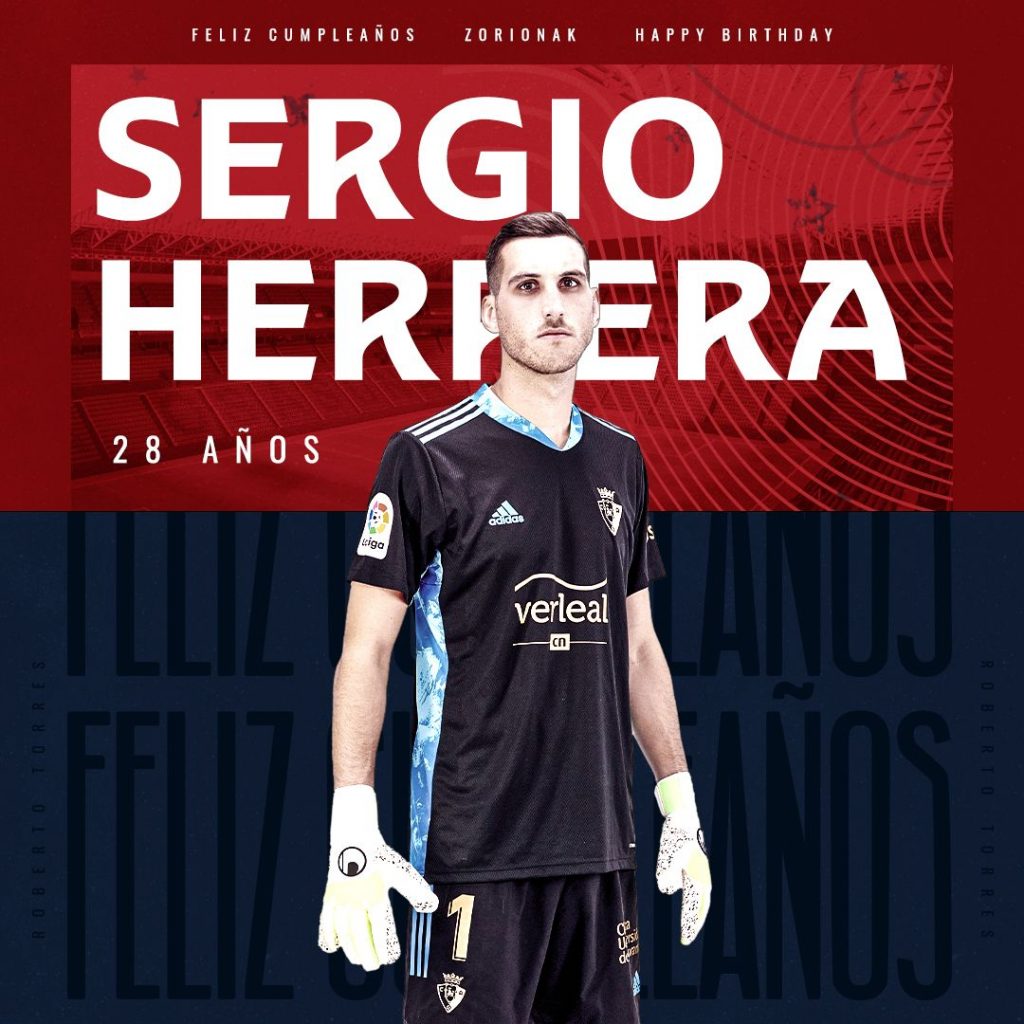
Con motivo del centenario de la entidad, el Club Atlético Osasuna ha estrenado su nueva tipografía realizada por el estudio pamplonés Ashler Design.
Osasuna ha estrenado su nueva tipografía exclusiva (diseño de letras y números) realizada por el estudio pamplonés Ashler Design. Se trata de una tipografía diseñada exclusivamente para el club rojillo y que se ha bautizado como Osasuna Font. El cambio de tipografía no afectará al escudo del club, que seguirá siendo el mismo que hasta el momento.
La nueva tipografía se utilizará a partir de ahora en el logotipo de la entidad, así como en la línea gráfica de la temporada 2021-2022 que también se ha estrenado para redes sociales. Al mismo tiempo, estará presente en diferentes campañas de comunicación que realice el club y tendrá una versión propia para utilizarla en las camisetas oficiales de la próxima temporada cuando la normativa lo permita (amistosos o Copa del Rey, por ejemplo).
Por otro lado, en los partidos de LaLiga no se podrá utilizar. Asimismo, toda la señalética del reformado estadio de El Sadar ya se ha realizado incluyendo las nuevas letras y números diseñados para Osasuna por Ashler Design. «Es la primera vez en su centenaria historia —indican desde el club— que contaremos con una tipografía propia después de haber utilizado en los últimos años diferentes tipos de letras comerciales al alcance de cualquier usuario».
La entidad rojilla pretende actualizar su imagen y hacerlo con coherencia y respeto a sus orígenes, remarcando su identidad propia.
referencias
«Uno de los grandes retos del proyecto —cuenta Octavio Pardo de Ashler— es la falta de referencias históricas claras o literales de las que partir. Osasuna no ha tenido hasta ahora una cultura tipográfica particular y Navarra hasta donde sabemos, tampoco tiene referentes históricos muy claros o conocidos. Ese detalle no es baladí porque Osasuna es más que otra empresa de la zona. Por un lado tiene una ligazón con Pamplona y con Navarra muy profunda; por otro se trata seguramente de uno de los grandes embajadores de Pamplona y Navarra en el mundo sino el que más. Yo siempre cuento la anécdota que cuando viajo por ahí muchas veces cuando me preguntan de donde soy, no conocen Pamplona pero sí conocen Osasuna».
«Por tanto —continua Pardo—, se trataba de afrontar un proyecto de representación identitaria donde había que buscar las referencias en otros medios. El estudio de carteles históricos de los San Fermines y de la feria del toro fue infructuoso, y las conclusiones no fueron tampoco muy claras: estéticamente hablando responden a la tendencia del momento de cuando fueron creados, y en todos estos años de historia no ha habido un elemento formal claro que haya servido de articulador de la línea gráfica. Esto no es en sí mismo un problema sino simplemente constato el hecho. Sí que es cierto que aunque en las primeras propuestas que hice opté por ignorarlos, en la última y definitiva sí que hay algún carácter que se ha inspirado en los carteles, especialmente en los del primer cuarto de siglo».
el euskera
«Otro de los puntos más delicados era el tema del euskera. Como tipógrafo a mí me gusta e interesa mucho la grafía vasca, y creía que esta podía ser una gran oportunidad para implementarla en un proyecto corporativo. También creía que estratégicamente era muy interesante para Osasuna apropiarse de ese espacio gráfico antes que el Athletic de Bilbao, la Real Sociedad o el Alavés —los tres clubes utilizan sans serifs genéricas—. Sin embargo, había varias cosas que no podían obviarse. Por un lado y muy importante, Osasuna no es un equipo vasco, es un equipo navarro».
«Aunque en Navarra el euskera es idioma oficial, no es ni de lejos mayoritario. Al mismo tiempo, Osasuna es el único equipo de la Liga de Fútbol Profesional que tiene un nombre en euskera. Ante esta realidad, opté por una solución que hace referencia lejana a esta grafía. De tal modo, si alguien quiere encontrar la referencia la encontrará. Sin embargo, si analizas la gran mayoría de los caracteres individualmente no tienen nada que ver con la grafía vasca, así que el que no la quiera encontrar no la encontrará. Creo que este equilibrio y este juego de referencias sutiles es uno de los grandes éxitos del proyecto».
Nueva tipografía de Osasuna
«Quería una suave referencia al espíritu de los mejores Osasunas: agresivos, incómodos y aguerridos.»
Octavio Pardo, Ashler
solución con personalidad
«El resultado es una fuente que hace una vaga referencia a las fuentes incisas talladas en piedra. Pamplona tiene una relación muy intima con las murallas y la piedra. En el centro de la ciudad se encuentra el recinto amurallado de la ciudadela; el palacio de congresos se llama el Baluarte, y también hay unas murallas de piedra por el centro que son monumento nacional. La referencia a las incisas me permitió además afilar las letras. Quería una suave referencia al espíritu de los mejores Osasunas: agresivos, incómodos y aguerridos. No es una grotesca corporativa clásica porque creo que el proyecto no pedía eso, sino una solución más atrevida y con más personalidad.»
letras y números
Octavio Pardo ha explicado a Gràffica algunas de las particularidades de las letras y los números que forman la familia. «A la A le dediqué muchísimas horas. Aparte de que la A es mi carácter favorito y siempre es al que le dedico más horas, en este caso era un elemento clave, ya que en Osasuna hay dos. El flequillo es uno de los elementos más característicos del proyecto. También curvé ligeramente las patas para que se relacionaran morfológicamente mejor con el escudo del club. Esos elementos junto a otros como las diagonales de M, N o V, harán la fuente inconfundible en cualquier comunicación que haga el club.
«Las fuentes corporativas siempre tienen que tener algo que resalte, para que justifiquen su valor comunicativo.»
Octavio Pardo, Ashler
«Por últimos los números. El proyecto tiene dos sets de números —de momento— porque ademas de la fuente corporativa también hemos hecho en el estudio el diseño de la señalización del estadio. El club quería que usáramos la fuente pero nos dimos cuenta de que el peso y la anchura de la fuente corporativa producía unos números demasiado contundentes para la señalización de espacios. Por tanto diseñé un set nuevo más condensado, un poquito más ligero y menos redondeado».
Octavio Pardo, el encargado del proyecto, se encuentra en la actualidad terminando un doctorado en legibilidad y tipografía para la Academia Real de las Artes de Copenhague. Ha sido asesor de Google fonts, y ha impartido cursos de tipografía en Media Lab del MIT, La Salle School of Design en Singapur, o en la Universidad de Ciencia y Tecnología de Noruega, entre otros.